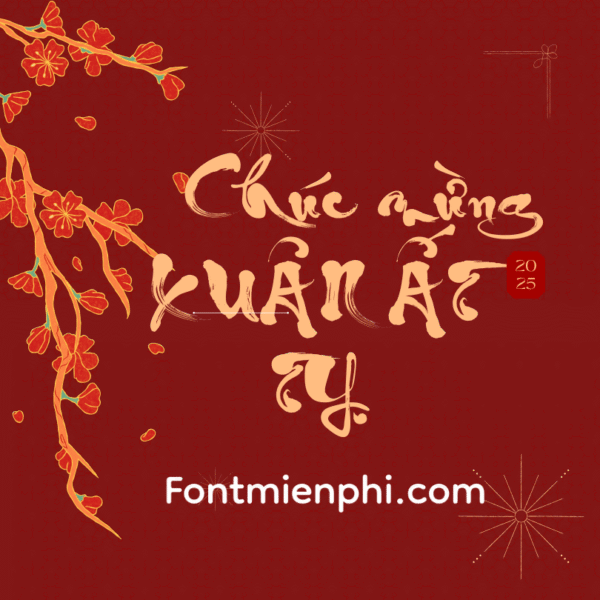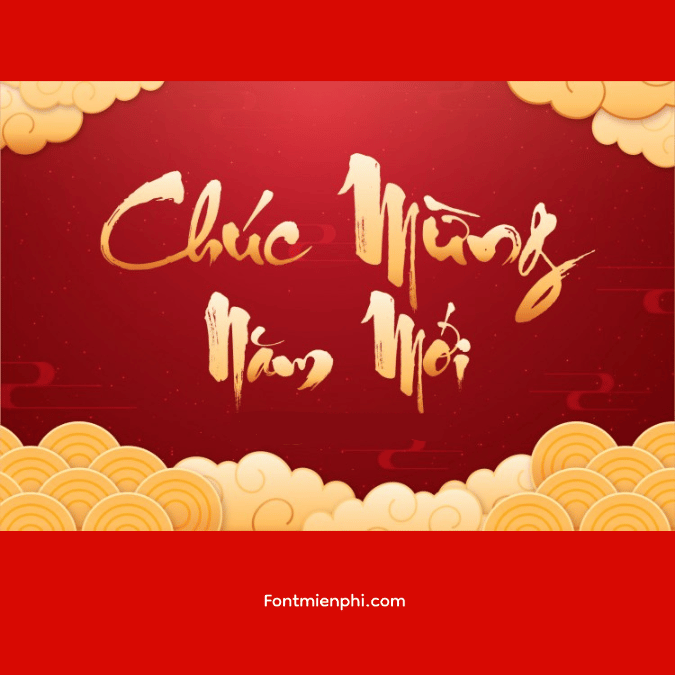
Font thư pháp UTM Thư Pháp Thiên Ân ,font Tết
Font thư pháp UTM Thư Pháp Thiên Ân là bộ Font chữ thư pháp UTM Thiên Ân do phát triển, sử dụng hầu hết ký tự thư pháp của thư pháp gia Đăng Học với những nét vẽ thư pháp trông giống như hàng thật được tạo ra bởi những ông đồ xưa. Font chữ Thiên Ân sở dĩ có tên như vậy bởi đây là một sản phẩm do chính tác giả tạo ra để tặng sinh nhật con trai Thiên Ân của mình. Người dùng có thể tải về, giải nén và sử dụng để phục vụ cho các nhu cầu cá nhân như thiết kế các tác phẩm áp phích nghệ thuật. Font UTM do anh Đinh Kiên Việt hóa chỉ được phép sử dụng với Mục đích cá nhân. Không được phép dùng cho thương mại. Để dùng thương mai vui long liên hệ tác giả để được phép.
Font Thư Pháp UTM Thư Pháp Thiên Ân và Font Tết
1. Font UTM Thư Pháp Thiên Ân
Font UTM Thư Pháp Thiên Ân là một loại font chữ thư pháp được thiết kế đặc biệt để thể hiện vẻ đẹp của chữ viết truyền thống Việt Nam. Đặc điểm nổi bật của font này bao gồm:
• Phong cách nghệ thuật: Chữ viết có nét uốn lượn mềm mại, mang lại cảm giác nhẹ nhàng và trang nhã.
• Sử dụng: Phù hợp cho việc thiết kế thiệp mời, banner, hoặc các sản phẩm liên quan đến văn hóa, lễ hội.
• Tính linh hoạt: Có thể sử dụng cho nhiều loại văn bản khác nhau, từ lời chúc Tết đến các bài thơ.
2. Font Tết
Font Tết là một loại font chữ được thiết kế riêng cho dịp Tết Nguyên Đán, mang đậm không khí lễ hội và truyền thống văn hóa Việt. Những đặc điểm chính của font này bao gồm:
• Hình ảnh mùa xuân: Các ký tự thường được trang trí với họa tiết hoa mai, hoa đào, hoặc các biểu tượng của sự thịnh vượng.
• Màu sắc tươi sáng: Font thường đi kèm với màu sắc rực rỡ, tạo nên không khí vui tươi, phấn khởi.
• Ứng dụng: Thích hợp cho việc tạo thiệp chúc Tết, poster quảng cáo, và các trang trí trong dịp lễ.
Cả hai loại font này đều góp phần làm phong phú thêm văn hóa chữ viết và nghệ thuật truyền thống của Việt Nam, đồng thời mang lại những cảm xúc tích cực trong các dịp lễ hội.